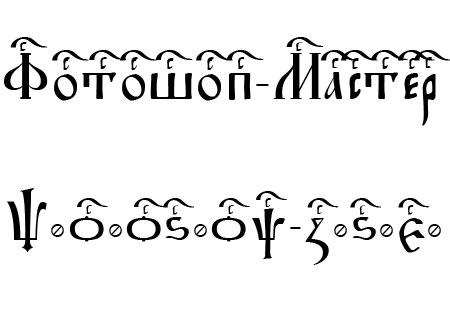
Дополнения Шрифты Татьяна Гапонова 8 июня 2009 Шрифт - IRMOLOGION SLOVO TITLED Старославянский шрифт, вместо английского написания - знаки. Скачать Шрифт - IRMOLOGION SLOVO TITLED